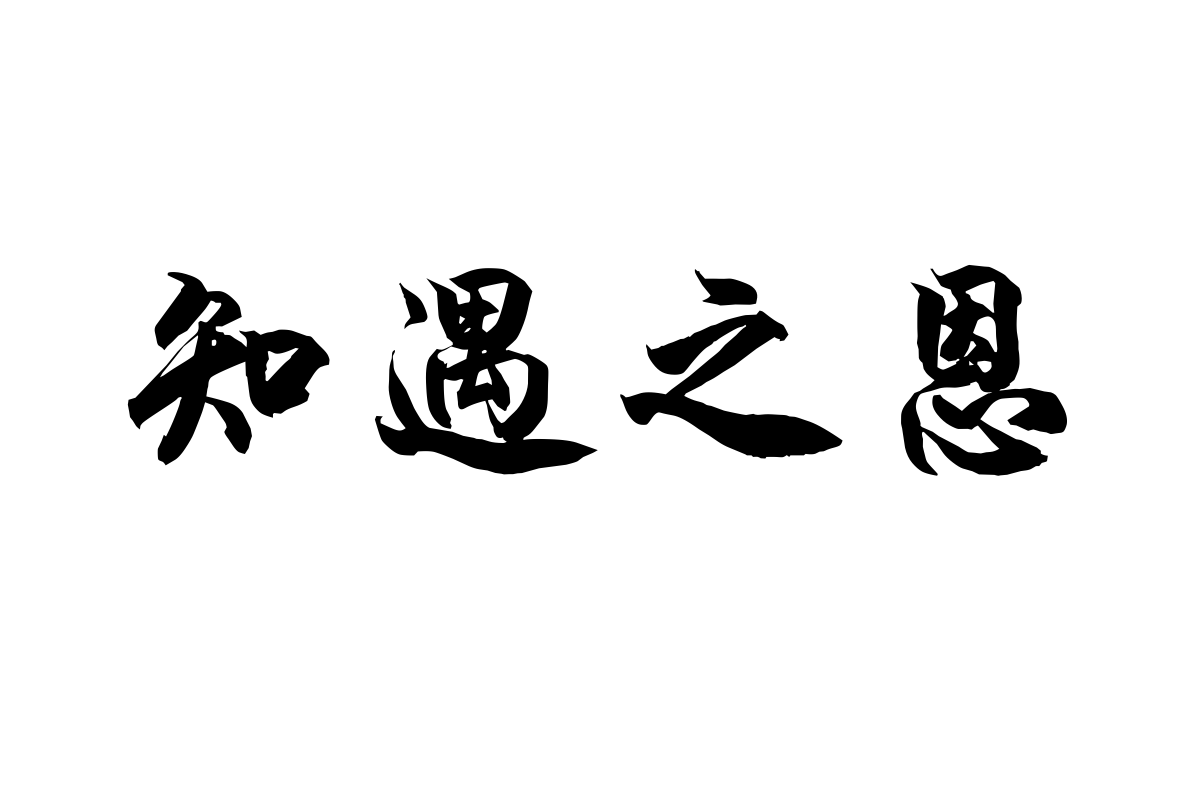
汉仪雪君体是一套适用于中文字体的字库,由汉仪公司设计。这套字体以其独特的风格和优雅的线条而受到广泛欢迎。汉仪雪君体的特点包括:
1. 字形优美:汉仪雪君体的字形独特,线条流畅,给人一种优雅的感觉。
2. 字体大小适中:汉仪雪君体的字体大小适中,适合各种场合使用,无论是标题、正文还是广告宣传等。
4. 易于使用:汉仪雪君体提供了丰富的字体样式和排版选项,用户可以根据自己的需求进行定制和调整。
5. 适用范围广:汉仪雪君体不仅适用于商业广告、海报、宣传册等印刷品,还适用于网页、手机屏幕等数字媒体的显示效果。
总之,汉仪雪君体是一款具有独特风格和优秀表现力的中文字体,适用于各种应用场景,深受设计师和用户的喜爱。